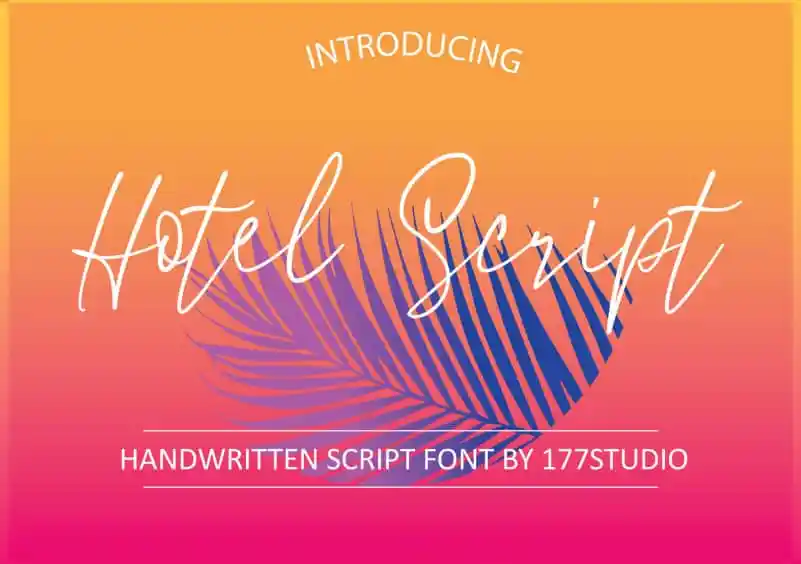
Hotel Handwritten Font – Fonte Grátis
Hotel Handwritten Font
A fonte “Hotel Handwritten Font” é uma elegante mistura de script, perfeita para aqueles projetos que buscam um toque natural e autêntico no estilo da escrita. Com seu personal touch de movimento fluido, ela oferece a oportunidade de trazer um pouco mais do seu jeito especial aos seus trabalhos gráficos. Este fonte é perfeito tanto para criações de marca, logotipos, designs para casamentos, postagens no Instagram e mídia digital, anúncios, embalagens de produtos, projetos de produtos, etiquetas, fotografias, marcas, convites, decoração de festa, bem como qualquer projeto que exija um sabor aveludado da escrita manual. A fonte “Hotel Handwritten Font” é uma escolha perfeita para quem busca um gráfico autêntico e sofisticado, com uma sensação natural e envolvente.